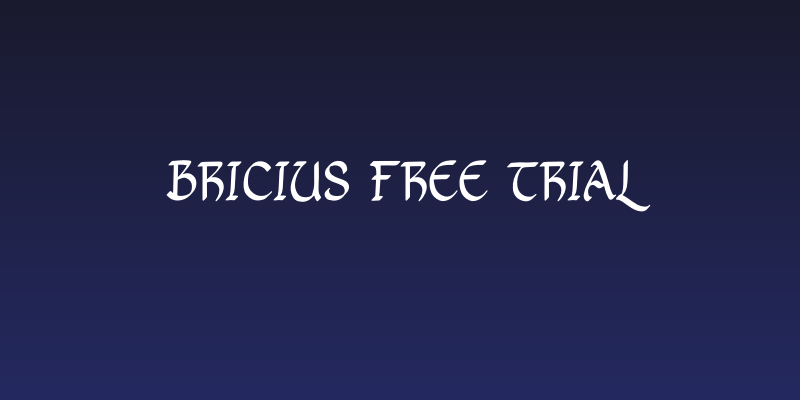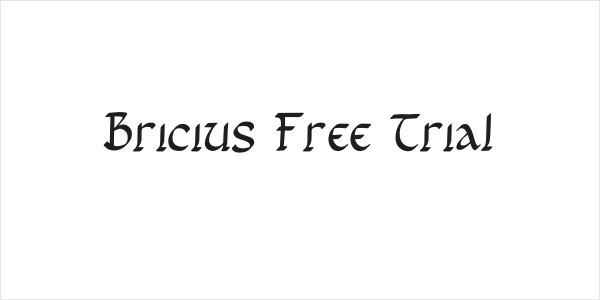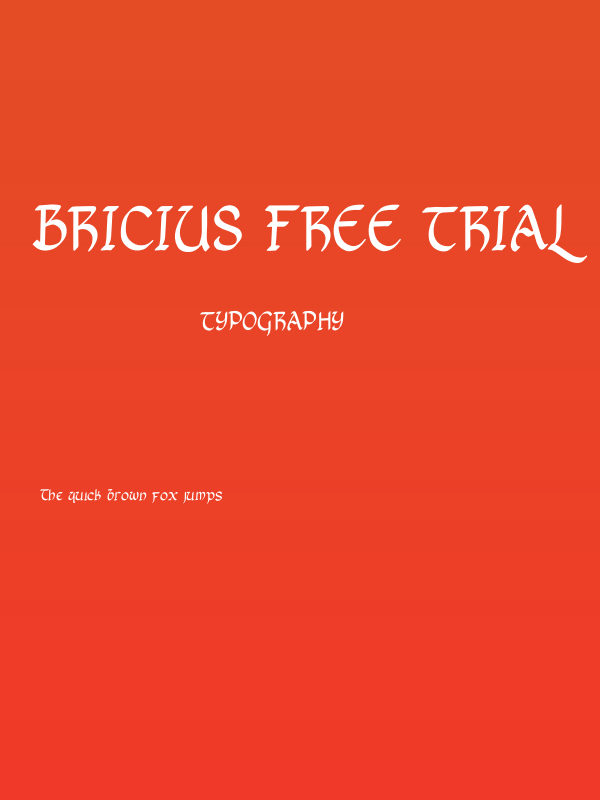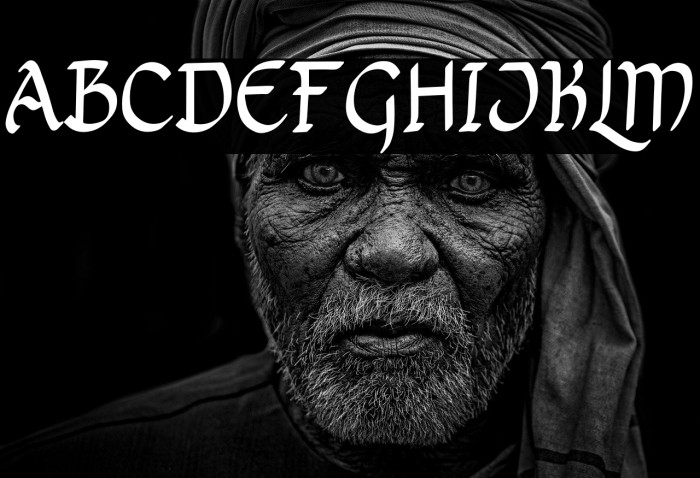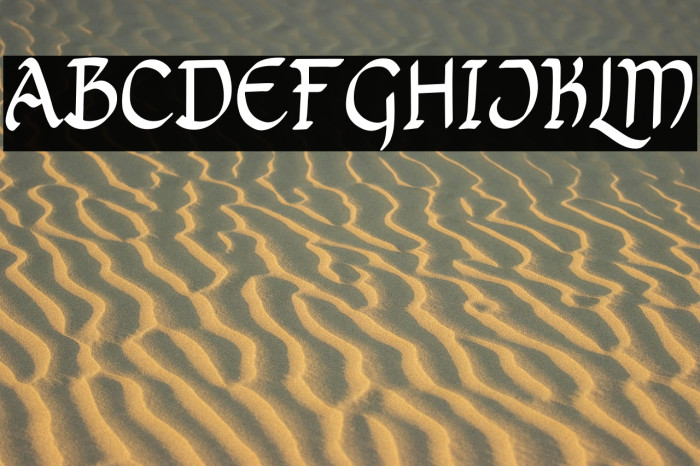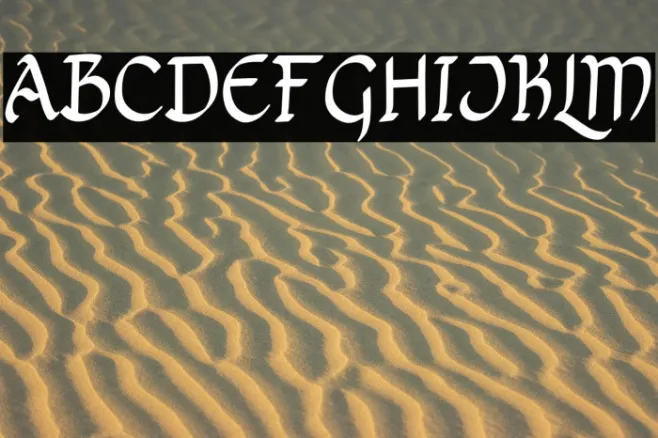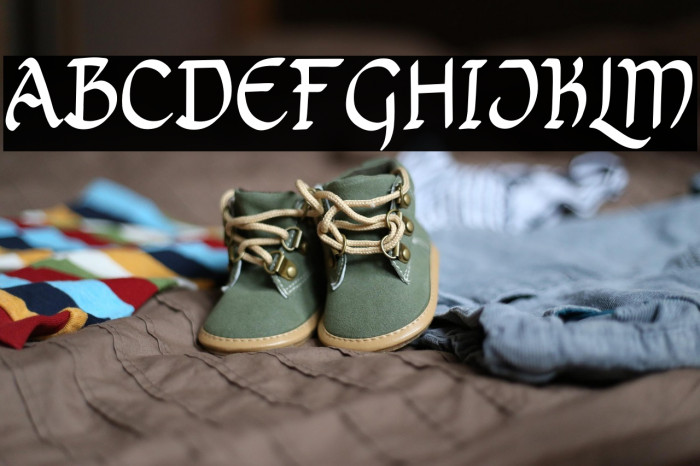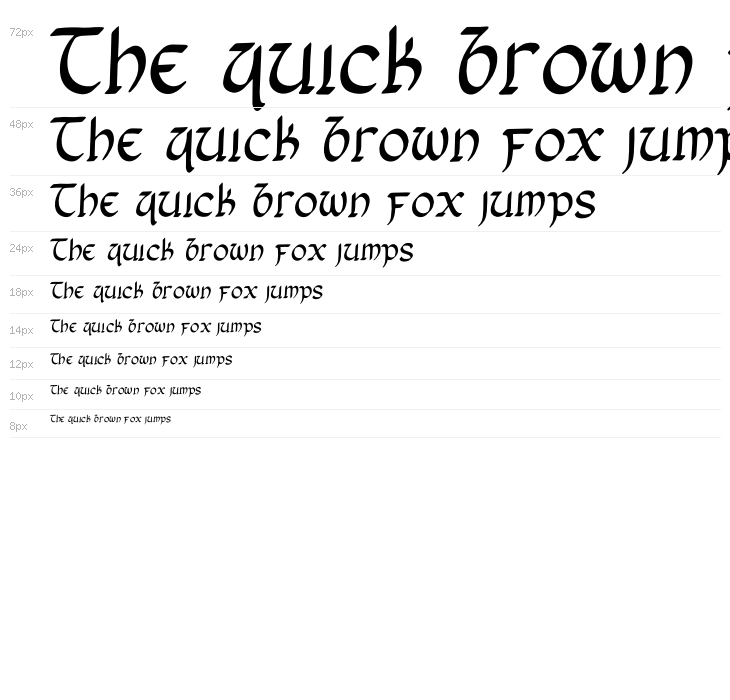
Bricius Free Trial Font
✎ Calligraphic
| Gesamtstil | Classic |
| Anwendungsfall | Logos, Invitations, Decorative text |
| Vorgeschlagene Projekte | Ideal for wedding invitations, historical documents, book covers, and branding that requires a traditional touch. |